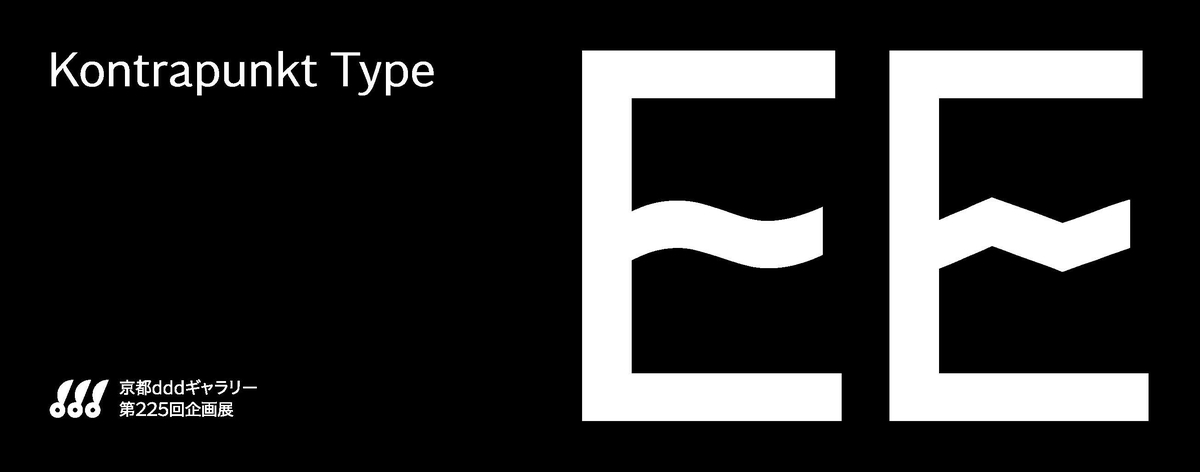
デザインエージェンシーがKontrapunkt Type(コントラプンクトタイプ)のバーチャル展覧会を開始
東京銀座にあるggg(ギンザ・グラフィック・ギャラリー)でオーダーメイドの書体のインタラクティブな展示が成功したことで、デザインジェンシーのKontrapunkt (コントラプンクト)は、2020年4月からの京都dddギャラリーでの個展「コントラプンクト タイプ」へ向けての準備を進めていたが、新型コロナウイルスの状況下延期になっていた。
このたび緊急事態宣言の解除を受け、京都ddd ギャラリーは2020年6月9日に再開した。
再開と共に、自宅やそれぞれのコンピュターから誰もがオンラインで楽しめるバーチャル展示の日本語版もオープンした。
Kontrapunkt Type(コントラプンクトタイプ)
これまでに多数の企業のオリジナルのタイプデザインを手がけてきたKontrapunkt(コントラプンクト)。
「私たちにとって、タイプ(書体)デザインは彫刻のように物語る一つの形であり、しかもそのストーリーはここで終わるのではありません」とコントラプンクトのボー・リネマン氏はコメントしている。
彼らが手がけた10のプロジェクトを紹介する今回の展覧会を通じて、今一度、書体に対する見方を考え直し、日々それとなく使っているタイプデザインに違った見方ができるようになり、一人一人がタイプデザインを見直す機会になればと思っているとのこと。
Kontrapunkt Type(コントラプンクトタイプ)バーチャル展
新型コロナウイルスの世界的な流行により、自宅で過ごす時間が長くなっている最近の日々がより有意義で充実感のある時間になるよう、また世界中どこからでも鑑賞して楽しんでもらえることを願って制作された。
テクノロジーを駆使して、できる限り実際の展示に近づけるようにしたいと言うのが始まりでした。
サイトの制作は大変でしたが、この状況の中でもたくさんの人に展示を見て欲しいと言う思いが優っていました。
できるだけ、実際の会場にいるように、インタラクティブにできるように設計しています。(Kontrapunkt デジタルデザイナー談)
Concept(タイプフェイスのコンセプトの投影)
Specimen (書体見本)
Spotlight (スポットライト)
Application (実例)、もしくは、Extra (その他)
の4つをモーションで見られます。
▼Asicsの例
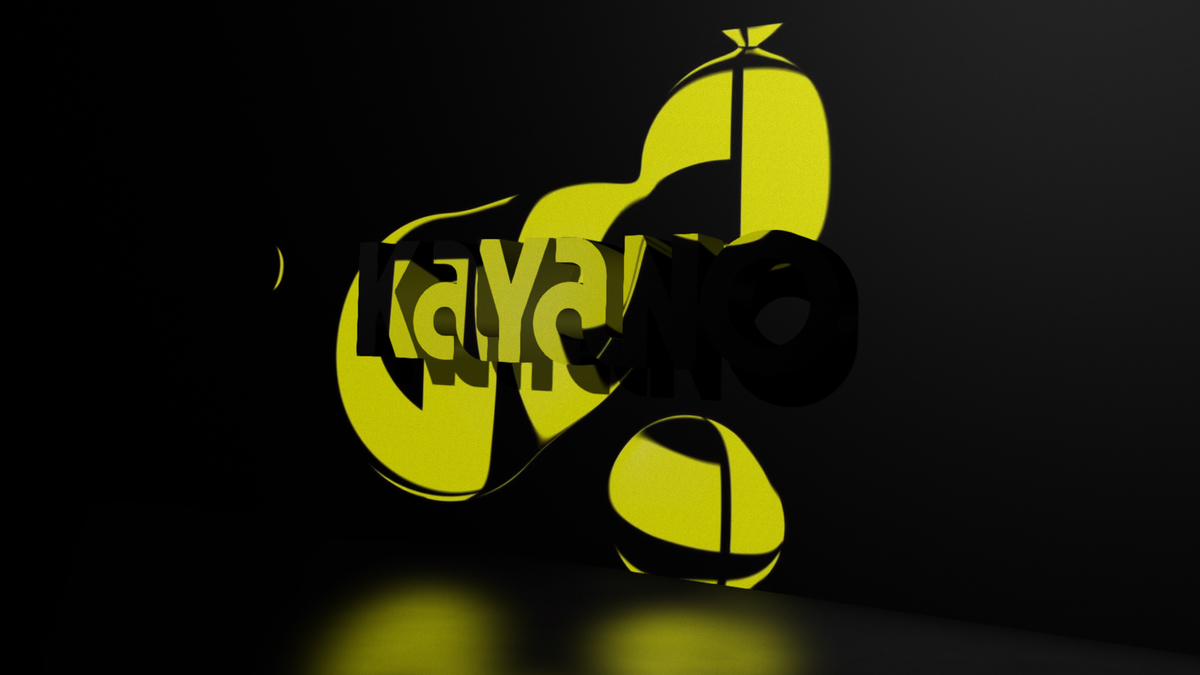
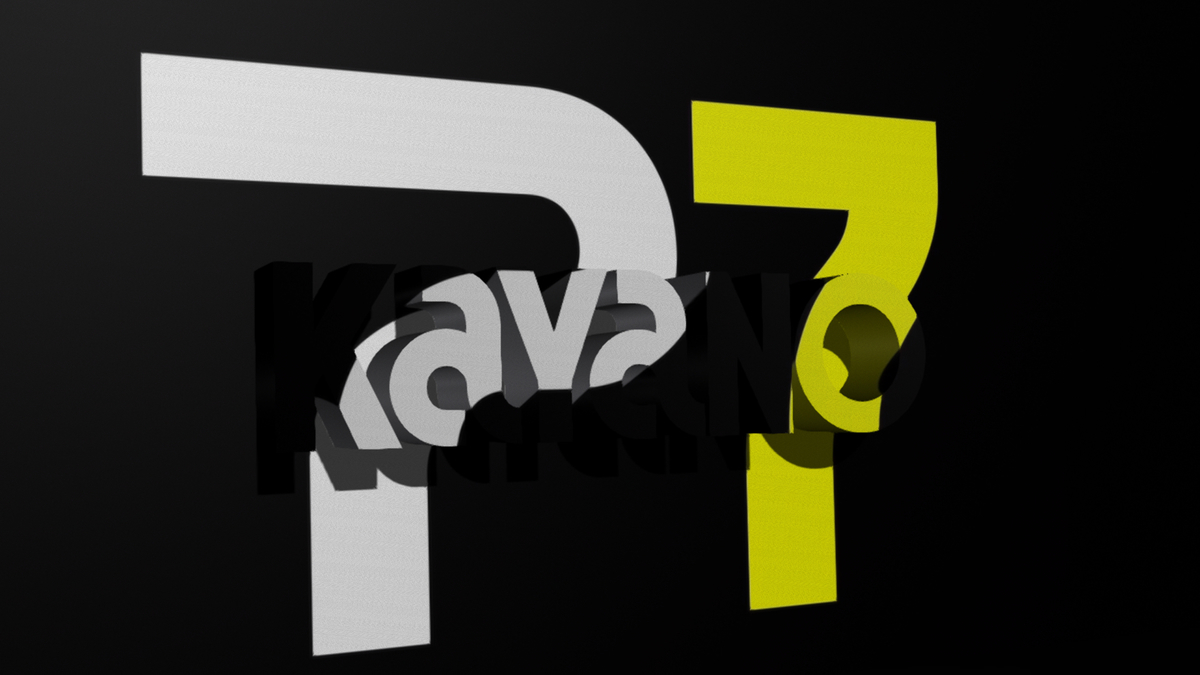
実際の展覧会では、来場者がペダルを踏んで楽しむ事ができるようになっている。
Kontrapunkt ステートメント
ブランド独自の書体は、多言語にマッチし、国境を越え、文化の架け橋となります。これは創り出された時から世界に通じ、多言語に適していますが、そのボイスや特徴は変わりません。叫ぶこともあれば囁くこともあり、実用的だったり、遊び心に満ちていたり。グローバルでありながら、本質的に、時・場所・族に特有のものです。
書体は、それぞれ独自のストーリーが込められたブランディングの要素の1つです。私たちはストーリーを文字のデザインで語ります。北欧特有の感覚を暗示し、ホップの葉をシンボルとして表したり、音の響きや象徴的なロゴからヒントを得たりするのです。書体が形作る言葉だけでなく、ブランドの特徴そのものも伝えるのは、こうしたディテールです。アルファベットのすべての要素が、さらなるストーリーを生み出すたくさんの語り口を持っているので、私たちはそれぞれの文字を独立したスカルプチュア(彫刻)として扱っています。私たちにとって、タイプ(書体)デザインは彫刻のように物語る一つの形であり、しかもストーリーはここで終わるのではありません。書体に対する
見方を皆様と共有できるこの機会を得られたことは大変光栄で、心から嬉しく思っております。
Kontrapunkt
北欧のリーディングデザインエージェンシー。35年の歴史の中で、政府機関、インフラ、NGO、文化団体から大企業に至るまで、多数のブランディングを手がける。世界中のデザイン賞も多数受賞。グラフィックデザインから、空間デザイン、タイポグラフィ、デジタルと多岐にわたるエリアのデザインでブランディングを一貫して手がけている。
2015年には日本法人も設立。機能美がありつつ、心の琴線に触れるデザインを基本とし、国境や文化を超え、時を超えるようなデザインを得意とし、デンソー、日産自動車、三菱自動車工業、資生堂、アシックス等、多数の日本の企業もクライアントに持ち、グローバルブランドへの一旦を担う。